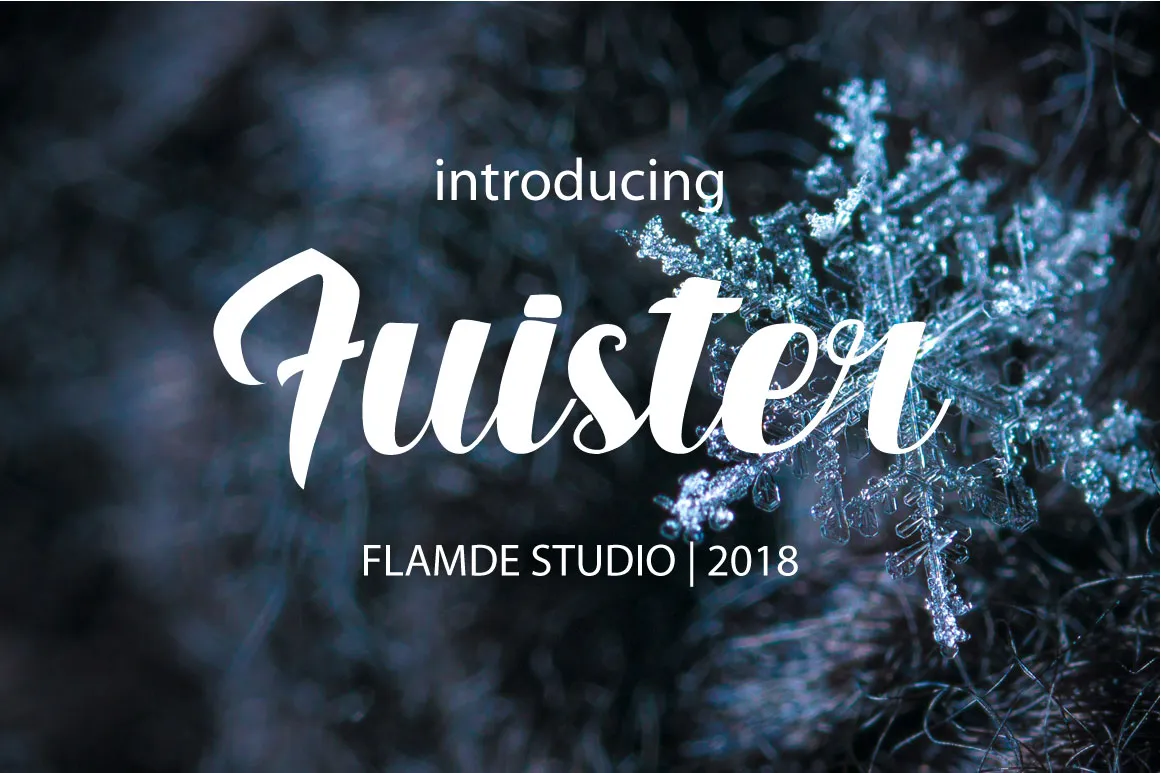
Fuister Script Font – Fonte Grátis
Fuister Script Font
A Fuister Script Font é uma grata surpresa para todos os apaixonados por letras livres e estilos elegantes. Criada pelo Flamde Studio, esta fonte é perfeitamente adequada para diversas aplicações gráficas. Suavemente fluida e repleta de detalhes meticulosos, ela pode ser usada em logotipos, roupas, revistas, panfletos, citações e muito mais. Com sua personalidade única e sofisticada, a Fuister Script Font traz elegância para qualquer projeto visual que você estiver criando. Além de suas aplicações usuais, esta fonte também é uma ótima escolha para aqueles projetos que buscam um toque diferente e único. Aproveite a beleza fluida da Fuister Script Font em sua próxima criação gráfica!